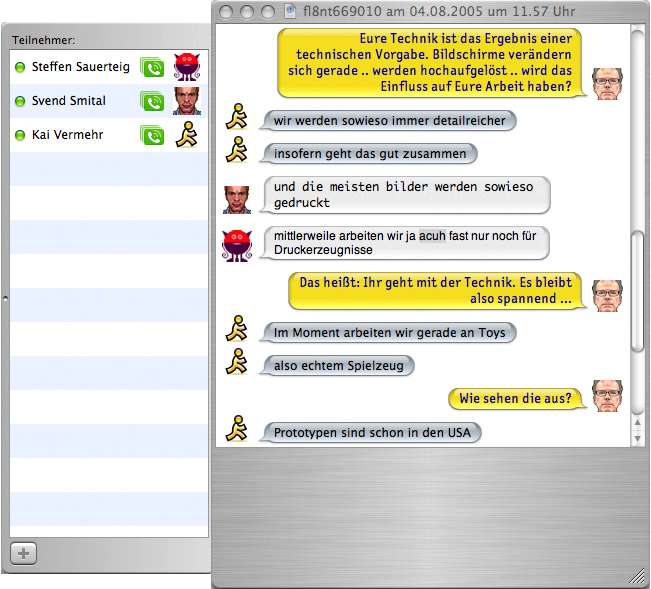
eBoy: »Kinder und Frauen sind immer heikel.«Am Anfang war das Pixel. Dann schufen sie Menschen, Monster und Maschinen.
Das Ende vom Lied: ein kindlich-brutaler Digitalkosmos, der sich unendlich weit
ausbreitet. Das Bitmap-Babylon der Berliner Designertruppe eBoy gilt als die
beste Pixel-Art im WWWeb. Das eBoy-Interview: über Jecken &
Microjecken, Pixelkunst, Type und Toys.
![]() Das Fontblog-Interview mit eBoy fand vor einer Woche per iChat-Konferenz statt (Text-Modus). Diese Technik hat unmittelbaren Einfluss auf die Form des Gesprächs: kurze Antworten, Stichwörter, SMS-Style. Da sich die Gesprächspartner keine visuellen Signale geben können, äußern sich alle Teilnehmer gleichzeitig. Fragen und Antworten mischen sich – auf den ersten Blick – zu einem Aneinandervorbeireden: es kommen meist zwei oder drei ähnliche Antworten auf eine Frage. Doppelte Inhalte, sich überschneidende Reaktionen und verzögerte Entgegnungen wurden in der Nachbearbeitung in den richtigen Kontext gebracht. ![]() In ganzer Länge (and also in English) finden Sie das Gespräch in der Ausgabe 12 des Online-Magazins Encore: Deutsches Encore Ausgabe 12 Englisches Encore Ausgabe 12 Hier im Fontblog konzentrieren wir unsere Befragung auf die Kunst der Minimal-Portraits, die »Jerks« (Jecken, Knallköpfe). Beim Preisausschreiben 15 Jahre FontShop hat die Berliner Designerin Catrin Schmitt ihr Portrait aus den Händen von eBoy gewonnen. ![]() eBoy (Kai Vermehr, Steffen Sauerteig, Svend Smital, Peter Stemmler) und Frau Schmitt (Catrin) Fontblog: Vor rund 3 Jahren habt Ihr eine Serie von Bitmap-Portraits im Maßstab 70 x 100 Pixel gestartet, die »Jerks«. Was war der Auslöser für diese Kunstform? Kai: Die Fahndungsbilder zum Anschlag vom 11. September. Steffen: Und ein Buchprojekt, zu dem wir eingeladen waren Kai: Es gab eine eigens eingerichtete Website, auf der die Fahndungsbilder des FBI alle zu finden waren. Fontblog: Die Fahndungsbilder gaben den Gesichtsausdruck vor. Wie kam es zu Format und Zeichentechnik? Kai: Das Format kommt vom Passbild, der frontale Anblick ... Steffen: ... die Technik ergab sich aus unserer Art zu arbeiten. ![]() Die ersten (anonymen) Jerks: Fahndungsbildern nachempfunden Fontblog: Sorry, falsch gefragt: Ich meinte die Auflösung der Jerks. Warum 70 x 100 Pixel? Kai: Ich weiß auch nicht mehr warum ... Ich glaube, die Auflösung hat sich aus den Original-Website-Portraits abgeleitet. Unsere Jerks sollten etwa genauso groß sein. Fontblog: Und die Auflösung ist direkt proportional zum Arbeitsaufwand ... das könnte auch eine Rolle gespielt haben: 140 x 200 heißt viermal mehr Arbeit, oder? Kai: Das stimmt allerdings. Fontblog: Könntet Ihr mal kurz die Arbeitsschritte einer Jerk-Produktion skizzieren? Der Ausgangspunkt ist ja wohl eine Fotografie, oder? Kai: 1. möglichst frontales Foto, 2. Spiegeln um die vertikale Achse; dabei werden aber unterschiedliche Teilbereich gespiegelt: links das Auge, rechts das Ohr, etc. Ziel ist, dem Original wieder etwas näher zu kommen. Fontblog: Ich habe selbst mal mit einem Passfoto herumgepixelt und gelernt, dass Eure Ergebnisse am Ende viel weiter weg sind von der Fotografie, als man glaubt. Manche Photoshop-Experten meinen, man könnte Jerks per Filter erzeugen ... Kai: Man kann sich manchmal mit PS-Filtern helfen, aber am Ende ist alles Handarbeit. Steffen: Das denken die Leute auch oft bei unseren übrigen Bildern, dass es da irgendwelche Filter gäbe ... da geht leider nichts automatisch. Kai: Unsere Arbeit ist wie Teppichknüpfen. Fontblog: Das Endergebnis ist eine Illustration mit photorealistischem Effekt und keine gepixelte Fotografie. Kai: Ja genau. Allerdings gefällt mir der Begriff Illustration nicht ... er hat etwas Begleitendes. Jerks sind Bilder, Icons. Sie stehen für sich. ![]() Freundschaftsdienste und Auftragsarbeiten: Paul Smith, Bruce Lee, der Fontblogger, seine Tochter Marie Fontblog: Die Faszination für Jerks ist ansteckend. Ihr habt auch schon Auftragsarbeiten gefertigt: Paul Smith ... kam der zu Euch oder Ihr zu ihm? Kai: Paul haben wir für Paul gemacht, als kleines Geschenk. Er hatte uns nach London eingeladen, zuvor besuchte er uns in Berlin. Fontblog: Nette Akquise ... Daraus ist eine spannende Kooperation geworden. Svend: Der Jerk war keine Akquise. Unsere Kooperation war schon vereinbart. Steffen: Er hatte in einem Londoner Buchladen unser Poster gesehen und fragte den Händler nach unserer Adresse. Fontblog: Hat Bruce Lee Euch auch eingeladen? Kai: (lacht) Svend: Bruce Lee war eine Auftragsarbeit ... für The Face, glaube ich. Steffen: Es war für Arena. Spezialausgabe zum Todestag. Man hatte einige Künstler hierzu eingeladen. Fontblog: Seit neuestem gibt es Microjerks. Warum das? Kai: Wir mussten eine ganze Menge Figuren für ein PS2-Magazin in den USA machen. Steffen: Die brauchten auf einen Schlag ganz viele Portraits. Mit der normalen Jerk-Technik wäre das zu aufwändig geworden. Kai: Wir mussten die Auflösung verringern. Das Ergebnis hat uns so gut gefallen, dass wir es als eigenes Produkt definiert haben. An den großen Jerks sitzt man relativ lange, bis sie wirklich gut sind. ![]() Microjerks, die neueste Erfindung von eBoy; die Portraitierten von links nach rechts: Masa Chatani, Larry Probst, Tetsuya Nomura, Tom Clancy, Kazunori Yamauchi, Ken Kutaragi, Ted Price und Fumito Ueda Fontblog: Wie lange, wenn ich fragen darf? Kai: Zwei bis drei Tage, manchmal sogar länger ... Dein Portrait war schwierig (lächelt). Fontblog: Danke. Und meine kleine Tochter Greta, glaube ich. Kai: Ja genau. Kinder und Frauen sind immer heikel. Das »tunen« kann viel Zeit kosten. Man muss ein Bild sacken lassen, und dann wieder dran arbeiten. Fontblog: Wenn man die Auflösung weiter herunterfahren würde, landete man bei den Minipops Flipflopflyin ... gibt es Kontakte zu Craig Robinson? Steffen: Ja, Craig ist ein Freund. Wir mögen seine Arbeit sehr. Kai: Wir spielen ab und zu Bowling oder Quake. Steffen: Und man trifft ihn oft auf Konzerten. Minipops von Craig Robinson: Arnold Schwarzenegger, Jimi Hendrix, Audrey Hepburn (als Holly Golightly), die Beatles, Adolf Hitler, The B-52’s Fontblog: Welche Bands? Steffen: Zuletzt bei Queens of The Stone Age. Fontblog: Habt ihr Euch gegenseitig beeinflusst oder seid Ihr unabhängig voneinander einen verwandten Weg gegangen? Kai: Unabhängig würde ich sagen. Steffen: Ja Kai: Er hat schon seinen eigenen Stil. Einer der wenigen Pixelmenschen, die wirklich einen eigenen Weg gehen. ... (mehr bei Encore) Herausgegeben: Do - August 11, 2005 at 08:50 vorm. | |